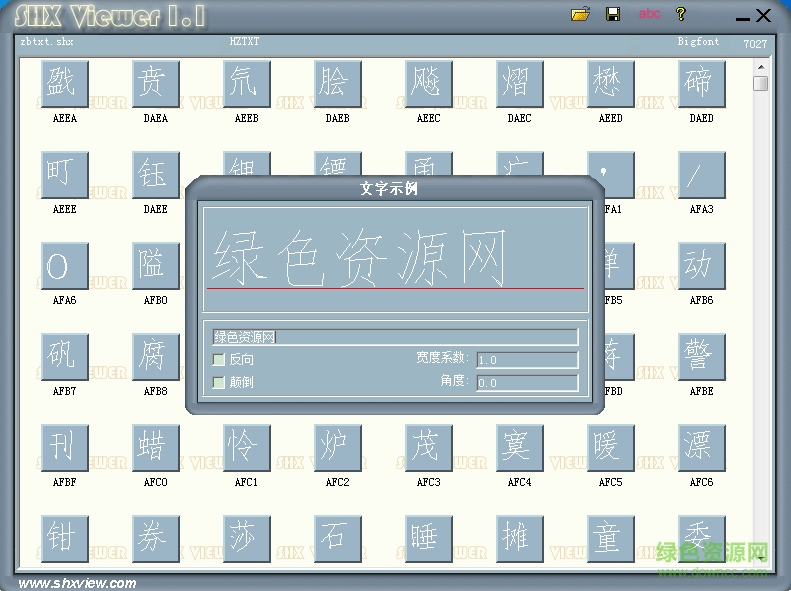
zbtxt.shx
zbtxt.shx是一款cad字體,這款字體主要解決cad圖紙因為缺少hzdxc.shx字體不能打開等問題,綠色資源網(wǎng)小編為您帶來zbtxt.shx免費字體下載,歡迎來本站下載使用。
常用的SHX字體介紹
Txt是最常用的小字體文件,包含數(shù)字、字母和一些簡單的符號,圖形比較簡單。
monotxt等寬的txt字體。在這種字體中,除了分配給每個字符的空間大小相同(等寬)以外,其他所有的特征都與 txt 字體相同。因此,這種字體尤其適合于書寫明細表或在表格中需要垂直書寫文字的場合。
romans這種字體是由許多短線段繪制的 roman 字體的簡體(單筆劃繪制,沒有襯線)。該字體可以產(chǎn)生比 txt 字體看上去更為單薄的字符。
romand這種字體與romans字體相似,但它是使用雙筆劃定義的。該字體能產(chǎn)生更粗、顏色更深的字符,特別適用于在高分辨率的打印機(如激光打印機)上使用。